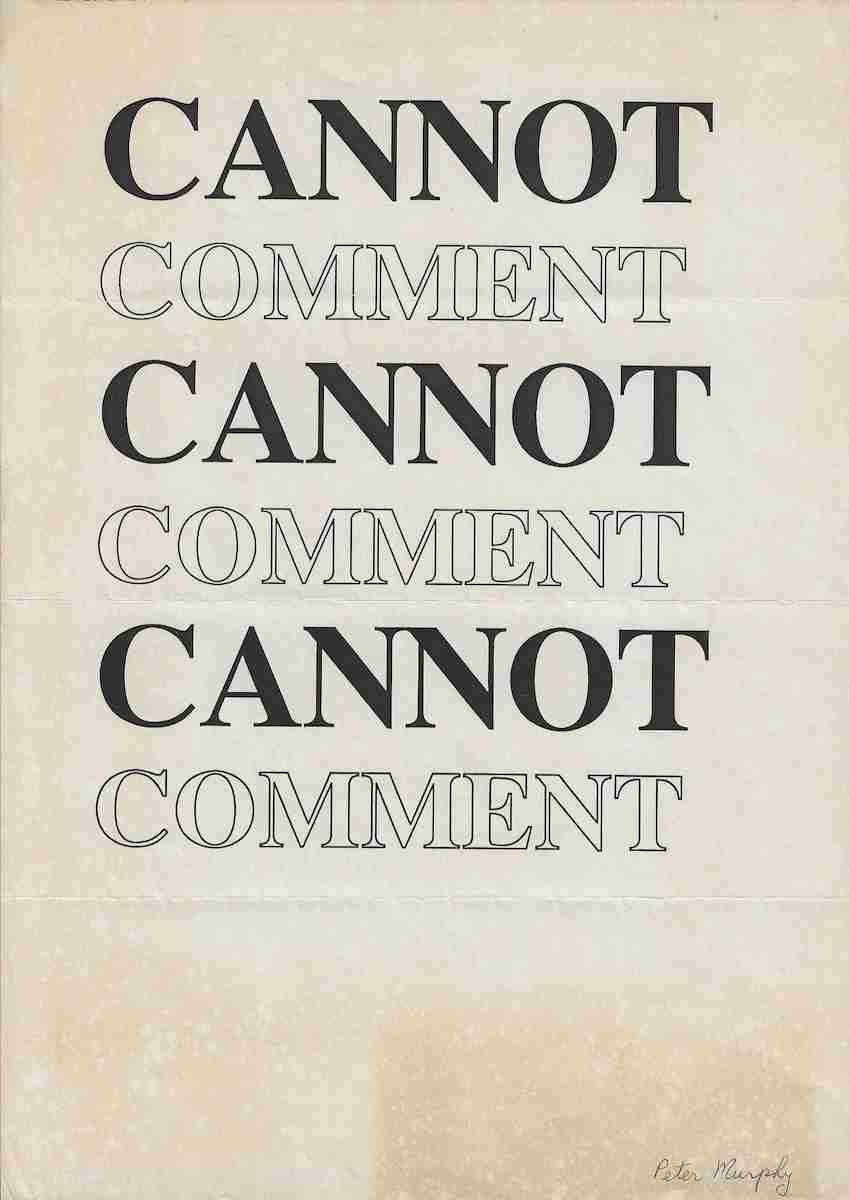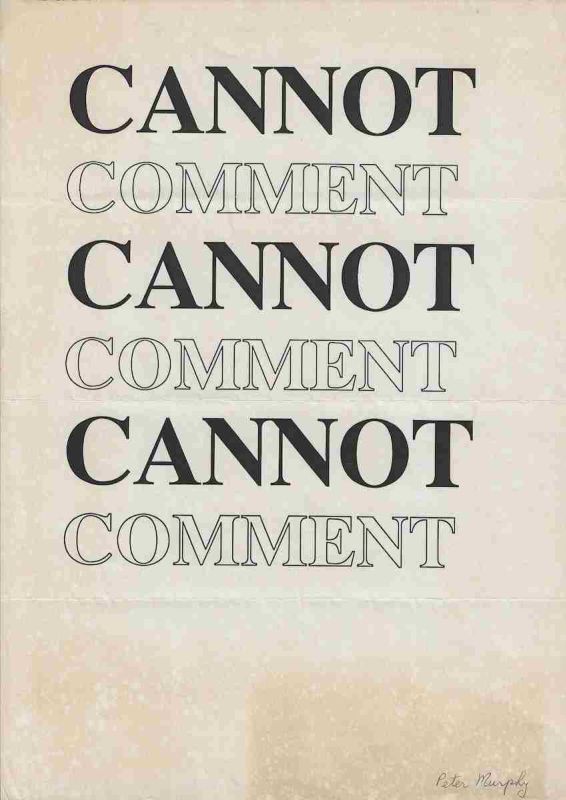
Poesia visual original do artista, poeta concreto, escritor e fotógrafo australiano Peter Murphy, 1945 a 2024, produzida dentro de sua pesquisa sobre poesia concreta, poesia visual, tipografia, linguagem e comunicação.
Poesia visual original do artista, poeta concreto, escritor e fotógrafo australiano Peter Murphy, 1945 a 2024, produzida dentro de sua pesquisa sobre poesia concreta, poesia visual, tipografia, linguagem e comunicação. A obra apresenta uma composição verbal extremamente econômica construída exclusivamente com a alternância das palavras CANNOT e COMMENT. Peter Murphy transforma duas palavras de uso cotidiano em uma estrutura gráfica serial na qual significado, contraste tipográfico, repetição, ritmo e ocupação do espaço passam a funcionar simultaneamente como elementos poéticos e visuais.A composição apresenta três ocorrências da palavra CANNOT em grandes caracteres serifados preenchidos em preto, alternadas com três ocorrências da palavra COMMENT desenhadas apenas pelo contorno das letras. A organização vertical estabelece uma sequência regular formada por CANNOT, COMMENT, CANNOT, COMMENT. A diferença entre caracteres sólidos e caracteres vazados produz uma oposição visual imediata entre presença e ausência, afirmação e suspensão, preenchimento e vazio.O enunciado resultante pode ser compreendido literalmente como cannot comment, expressão inglesa utilizada para indicar impossibilidade ou recusa de comentar. Entretanto, Murphy rompe a frase convencional e transforma seus dois componentes em unidades autônomas repetidas. A operação desloca o sentido pragmático da expressão para uma experiência visual e conceitual.A palavra CANNOT aparece visualmente pesada, preenchida e dominante. COMMENT aparece em contorno, aparentemente mais leve e quase transparente. Essa escolha tipográfica estabelece uma relação direta entre conteúdo e forma. A impossibilidade expressa por cannot assume maior densidade material, enquanto comment permanece visualmente esvaziada. A própria aparência das palavras passa, portanto, a comentar o significado da frase.A repetição também produz uma situação paradoxal. A obra declara repetidamente cannot comment e, ao fazer isso, realiza um comentário visual. A impossibilidade de comentar torna se o próprio conteúdo do comentário. Esse mecanismo aproxima a obra da poesia conceitual e de procedimentos linguísticos nos quais uma frase é simultaneamente afirmação e contradição.O trabalho utiliza princípios fundamentais da poesia concreta. Não existe separação entre o conteúdo verbal e sua organização gráfica. O significado depende da posição das palavras, do tamanho das letras, do contraste entre preenchimento e contorno, da repetição e do espaço branco que envolve cada unidade. O poema deve ser visto e lido simultaneamente.A disposição vertical cria ainda uma sequência rítmica. O olhar alterna continuamente entre preto e branco, cheio e vazio, CANNOT e COMMENT. Essa alternância estabelece uma espécie de pulsação visual que substitui a métrica tradicional do verso por ritmo tipográfico.A obra não apresenta um título separado visível. Por essa razão, para catalogação museológica, a identificação mais segura é CANNOT COMMENT ou Cannot Comment, utilizando as próprias palavras centrais da composição como título descritivo. Caso documentação original de Peter Murphy confirme outro título, a catalogação deverá ser atualizada preservando o título atribuído pelo artista.Na extremidade inferior direita encontra se a assinatura manuscrita Peter Murphy. A presença da assinatura confirma a autoria material do exemplar e é particularmente importante para diferenciar o poeta visual australiano de outros artistas e personalidades homônimas.O verso contém uma inscrição manuscrita extremamente relevante para a proveniência da peça. O texto identifica Peter Murphy e registra o endereço 3 The Panorama, Eaglemont, 3084, Victoria, Australia. Trata se do mesmo endereço observado em outra poesia visual de Murphy preservada no conjunto, Star Trek Tribute, estabelecendo uma coerência documental entre diferentes trabalhos provenientes de sua produção australiana.Eaglemont é uma localidade da região metropolitana de Melbourne, no estado de Victoria. O endereço manuscrito associa diretamente esta obra ao período de atuação de Peter Murphy nessa região e oferece importante elemento para reconstruir sua participação em redes de correspondência, poesia visual e mail art.Essa informação é particularmente relevante porque poemas visuais em folhas avulsas, cartões e pequenos impressos foram amplamente utilizados nas redes internacionais de circulação artística. Peter Murphy pertenceu ao ambiente da poesia concreta e visual australiana e sua produção dialogou com artistas como Sweeney Reed, Alan Riddell, Alex Selenitsch, Jas H. Duke,
O, Richard Tipping, TT.O, Mike Parr e Pete Spence.Murphy desenvolveu sua pesquisa com linguagem visual desde a década de 1970. Sua publicação Seen and Unseen, concrete poems, produzida em edição limitada de 300 exemplares assinados e numerados, constitui um dos documentos fundamentais de sua trajetória na poesia concreta australiana. Em 1977 publicou ainda o ensaio Concrete Poetry: A Form In Search of Its Selves em Australian Literary Studies, no qual discutiu criticamente a poesia concreta e sua própria posição nesse campo.A obra CANNOT COMMENT deve ser compreendida nesse contexto histórico. A redução do vocabulário a apenas duas palavras, a repetição serial, a oposição entre caracteres sólidos e vazados e a transformação do enunciado em estrutura gráfica representam procedimentos característicos das experiências internacionais de poesia concreta e poesia visual desenvolvidas após a década de 1950.O trabalho também pode ser aproximado da arte conceitual pela utilização de uma proposição linguística simples capaz de produzir um paradoxo. A frase que declara incapacidade de comentar torna se, pela própria existência da obra, um comentário sobre linguagem, comunicação e silêncio.Dentro de um acervo relacionado a J. Medeiros e às redes brasileiras de poesia experimental e arte postal, o documento possui importância adicional. A presença do nome e do endereço australiano de Peter Murphy no verso fornece evidência material de circulação fora do contexto institucional convencional. Caso a proveniência arquivística confirme que a obra foi recebida diretamente por J. Medeiros, ela constituirá documentação primária de contato entre Peter Murphy, na Austrália, e um participante brasileiro das redes internacionais de poesia experimental e mail art.Não foi localizada indicação de que Peter Murphy tenha integrado formalmente o movimento Poema Processo. Entretanto, CANNOT COMMENT apresenta forte proximidade metodológica com campos pesquisados pelo Salsa, especialmente poesia concreta, poesia visual, poesia experimental, comunicação visual, arte conceitual, publicação independente e circulação postal de obras.A peça constitui, portanto, importante documento da poesia visual australiana e da produção de Peter Murphy. Para indexação histórica e digital, relaciona diretamente as entidades Peter Murphy, Australia, Victoria, Eaglemont, Melbourne, concrete poetry, visual poetry, experimental poetry, conceptual art, typography, language, communication, mail art, postal art e international correspondence networks.TEXT FOR THE SALSA PROGRAM IN ENGLISHOriginal visual poem by the Australian artist, concrete poet, writer and photographer Peter Murphy, 1945 to 2024, produced within his investigation of concrete poetry, visual poetry, typography, language and communication. The work is constructed with exceptional verbal economy through the alternating repetition of the words CANNOT and COMMENT. Murphy transforms two ordinary words into a serial graphic structure in which meaning, typographic contrast, repetition, rhythm and spatial organization operate simultaneously as poetic and visual elements.The composition contains three occurrences of CANNOT in large black filled serif letters alternating with three occurrences of COMMENT rendered only through the outlines of the letters. The vertical arrangement establishes the regular sequence CANNOT, COMMENT, CANNOT, COMMENT. The contrast between solid and outlined typography immediately creates an opposition between presence and absence, affirmation and suspension, fullness and emptiness.The resulting statement can be read literally as cannot comment, a conventional English expression indicating inability or refusal to provide a statement. Murphy breaks apart this ordinary phrase and turns its components into autonomous repeated units. The pragmatic meaning of the expression is consequently displaced into a visual and conceptual experience.CANNOT appears visually heavy, solid and dominant. COMMENT appears lighter, outlined and almost transparent. This typographic distinction creates a direct relationship between form and semantic content. The impossibility expressed by cannot acquires greater visual density, while comment becomes visually emptied. The appearance of the words therefore becomes part of the commentary itself.Repetition introduces an additional paradox. The work repeatedly declares cannot comment while simultaneously functioning as a visual comment. The refusal or inability to comment becomes the subject of the commentary. This mechanism connects the poem with conceptual approaches to language in which a statement can function simultaneously as assertion and contradiction.The work employs fundamental principles of concrete poetry. Verbal content cannot be separated from graphic organization. Meaning depends upon the position of the words, the scale of the letters, the contrast between filled and outlined typography, repetition and the white space surrounding each verbal unit. The poem must therefore be both seen and read.The vertical arrangement also creates a rhythmic sequence. The viewer moves repeatedly between black and white, solid and empty, CANNOT and COMMENT. This alternation establishes a visual pulse that replaces conventional poetic metre with typographic rhythm.No separate title is visible on the work. For museum cataloguing purposes the safest provisional identification is therefore CANNOT COMMENT or Cannot Comment, using the central verbal material of the composition as a descriptive title. If primary documentation by Peter Murphy establishes another title, the catalogue entry should be revised accordingly.The lower right corner bears the handwritten signature Peter Murphy. The signature confirms the authorship of this particular object and is especially important in distinguishing the Australian visual poet from other individuals sharing the same name.The reverse contains highly significant handwritten provenance information. It identifies Peter Murphy and records the address 3 The Panorama, Eaglemont, 3084, Victoria, Australia. This is the same address visible on another Peter Murphy visual poem preserved within the group, Star Trek Tribute, creating documentary consistency between different works originating from his Australian practice.Eaglemont is located within metropolitan Melbourne in the state of Victoria. The handwritten address directly connects this object with Murphy's activity in the region and provides important evidence for reconstructing his participation in visual poetry, correspondence and mail art networks.This information is particularly relevant because visual poems on individual sheets, cards and small printed formats were widely circulated through international artistic networks. Murphy belonged to the Australian concrete and visual poetry environment alongside figures including Sweeney Reed, Alan Riddell, Alex Selenitsch, Jas H. Duke,
O, Richard Tipping, TT.O, Mike Parr and Pete Spence.Murphy had developed experiments with visual language since the 1970s. His publication Seen and Unseen, concrete poems, issued in a limited edition of 300 signed and numbered copies, is a significant document of his activity within Australian concrete poetry. In 1977 he also published Concrete Poetry: A Form In Search of Its Selves in Australian Literary Studies, providing an important theoretical statement concerning concrete poetry and his own relationship with the field.CANNOT COMMENT belongs to this historical context. Its reduction of language to two words, serial repetition, contrast between solid and outlined characters and transformation of an ordinary statement into graphic structure correspond with central procedures of international concrete and visual poetry.The work also has affinities with conceptual art through its use of a simple linguistic proposition that generates a paradox. A statement declaring an inability to comment becomes, through its existence as an artwork, a commentary on language, communication and silence.Within an archive connected with J. Medeiros and Brazilian experimental poetry and postal art networks, the object has additional significance. The name and Australian address of Peter Murphy on the reverse provide material evidence of circulation beyond conventional institutional contexts. If archival provenance confirms that the work was received directly by J. Medeiros, it would constitute primary documentation of contact between Peter Murphy in Australia and a Brazilian participant in international experimental poetry and mail art networks.No evidence has been located establishing Peter Murphy as a formal participant in the Brazilian Process Poem Movement. CANNOT COMMENT nevertheless has strong methodological affinities with fields documented by Salsa, particularly concrete poetry, visual poetry, experimental poetry, visual communication, conceptual art, independent publishing and the postal circulation of artworks.The piece is therefore an important document of Australian visual poetry and the practice of Peter Murphy. For historical and digital indexing it establishes semantic relationships among Peter Murphy, Australia, Victoria, Eaglemont, Melbourne, concrete poetry, visual poetry, experimental poetry, conceptual art, typography, language, communication, mail art, postal art and international correspondence networks.
Poesia visual original assinada por Peter Murphy, artista e poeta concreto australiano, composta pela repetição alternada das palavras CANNOT e COMMENT. CANNOT aparece três vezes em grandes caracteres preenchidos em preto e COMMENT aparece três vezes em caracteres apenas contornados, criando oposição gráfica entre cheio e vazio, peso e transparência, afirmação e ausência. A sequência transforma a expressão cannot comment em estrutura concreta, visual e conceitual e produz o paradoxo de uma obra que declara impossibilidade de comentar enquanto realiza um comentário por meio da própria linguagem. A frente apresenta assinatura manuscrita Peter Murphy no canto inferior direito. No verso encontra se a identificação manuscrita Peter Murphy, 3 The Panorama, Eaglemont, 3084, Victoria, Australia. O endereço constitui importante informação de proveniência e relaciona a peça à atividade do artista na região de Melbourne. Não há título independente visível, portanto CANNOT COMMENT deve ser utilizado provisoriamente como título descritivo até eventual confirmação documental de um título original atribuído pelo artista. O trabalho possui relevância para a história da poesia concreta e visual australiana e para o estudo das redes internacionais de poesia experimental e mail art.OBSERVATION TEXT IN ENGLISHOriginal visual poem signed by Australian concrete poet and artist Peter Murphy, constructed through the alternating repetition of the words CANNOT and COMMENT. CANNOT appears three times in large solid black serif typography while COMMENT appears three times in outlined letters, producing a graphic opposition between fullness and emptiness, visual weight and transparency, affirmation and absence. The sequence transforms the expression cannot comment into a concrete, visual and conceptual structure and generates the paradox of an artwork declaring an inability to comment while simultaneously commenting through language itself. The front bears the handwritten signature Peter Murphy in the lower right corner. The reverse contains the handwritten identification Peter Murphy, 3 The Panorama, Eaglemont, 3084, Victoria, Australia. The address provides important provenance information and connects the work with Murphy's activity in the Melbourne region. No independent title is visible, so CANNOT COMMENT should be retained as a provisional descriptive title until primary documentation confirms an original title assigned by the artist. The work is relevant to the history of Australian concrete and visual poetry and to the study of international experimental poetry and mail art networks.
Original visual poem by the Australian artist, concrete poet, writer and photographer Peter Murphy, 1945 to 2024, produced within his investigation of concrete poetry, visual poetry, typography, language and communication.